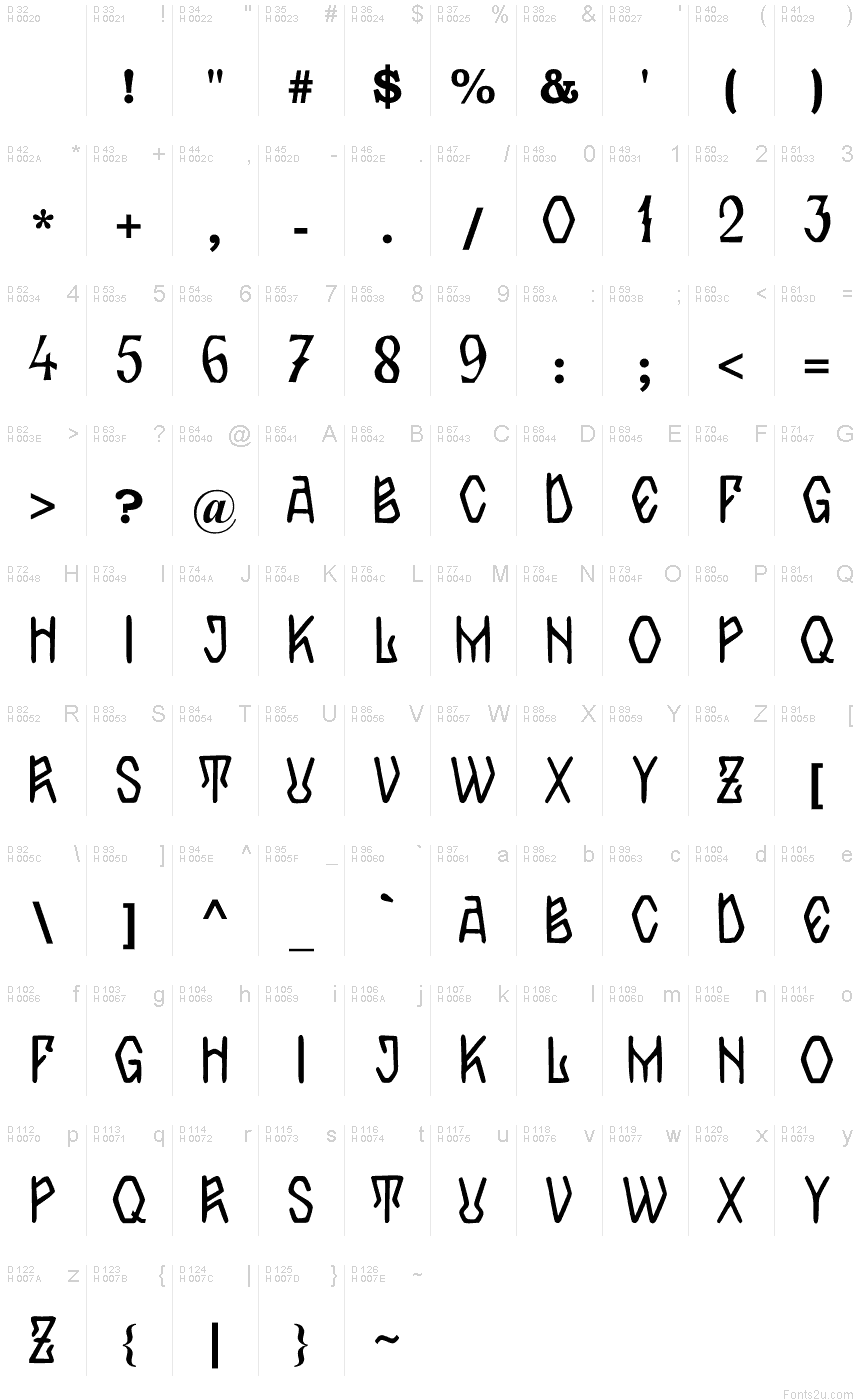
Zamolxis IV, stworzony przez Zamolxis, to darmowy krój gotycki (tylko wielkie litery) o surowym, średniowiecznym klimacie i wyglądzie wycinanym ręcznie. Litery opierają się na wysokich, wąskich formach, ostrych kątach i wyrazistych pociągnięciach, które są celowo nierówne, co nadaje czcionce szorstki, rzeźbiony charakter, w przeciwieństwie do wygładzonych krojów czarnoszeryfowych.
Pasuje do tytułów na plakatach, logotypów gier, okładek książek fantasy, ulotek festiwalowych i opakowań tematycznych, gdzie ten klimat dawnych czasów pozwala szybko nadać odpowiedni ton. Jako darmowy font, sprawdza się również w krótkich nagłówkach i monogramach, ponieważ wielkie litery mają wystarczająco dużo wyrazistości, by przyciągać wzrok bez potrzeby dodatkowych ozdobników.